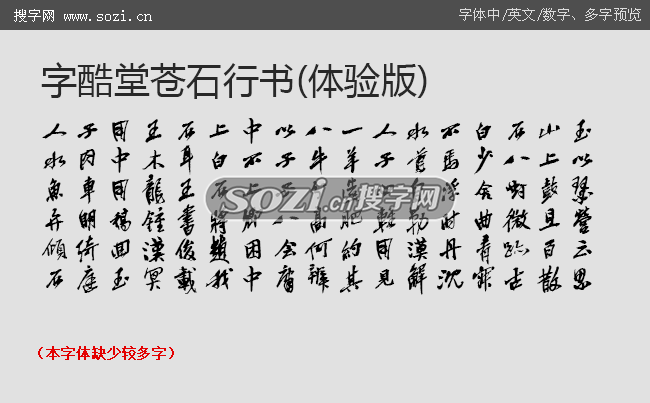
字酷堂蒼石行書(shū)(體驗(yàn)版)
搜字網(wǎng)提供一款字酷堂蒼石行書(shū)(體驗(yàn)版)手寫中文書(shū)法字體下載,字酷堂蒼石行書(shū)是一款非常漂亮的手寫字體,字體極具藝術(shù)風(fēng)格,每筆每畫都給人一種飄逸灑脫的感覺(jué),整體效果非常出色,能夠應(yīng)用于平面設(shè)計(jì)、名片設(shè)計(jì)、廣告創(chuàng)意、印刷等場(chǎng)合應(yīng)用。
- 風(fēng)格類別: 手寫書(shū)法體
- 完整程度: 缺少較多字